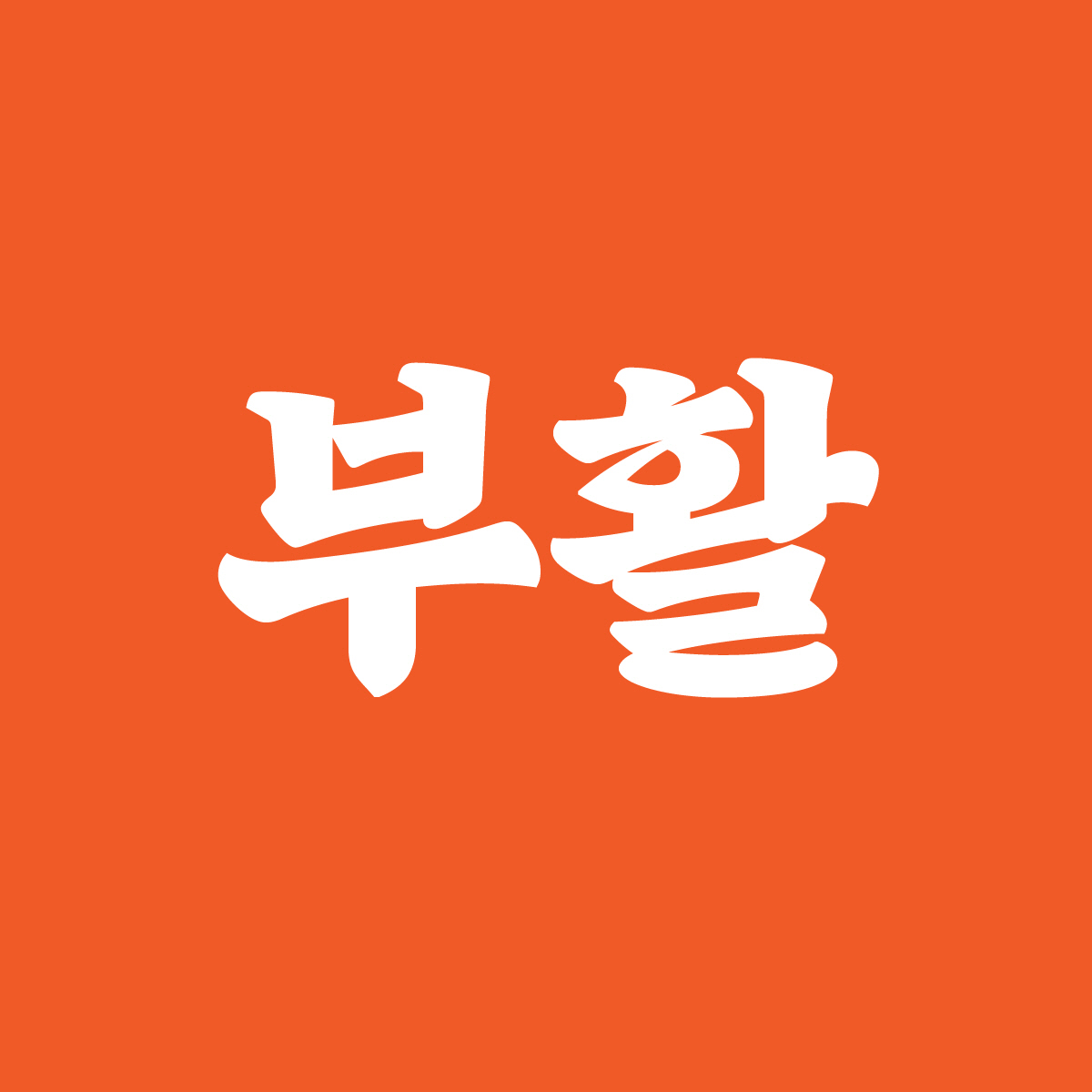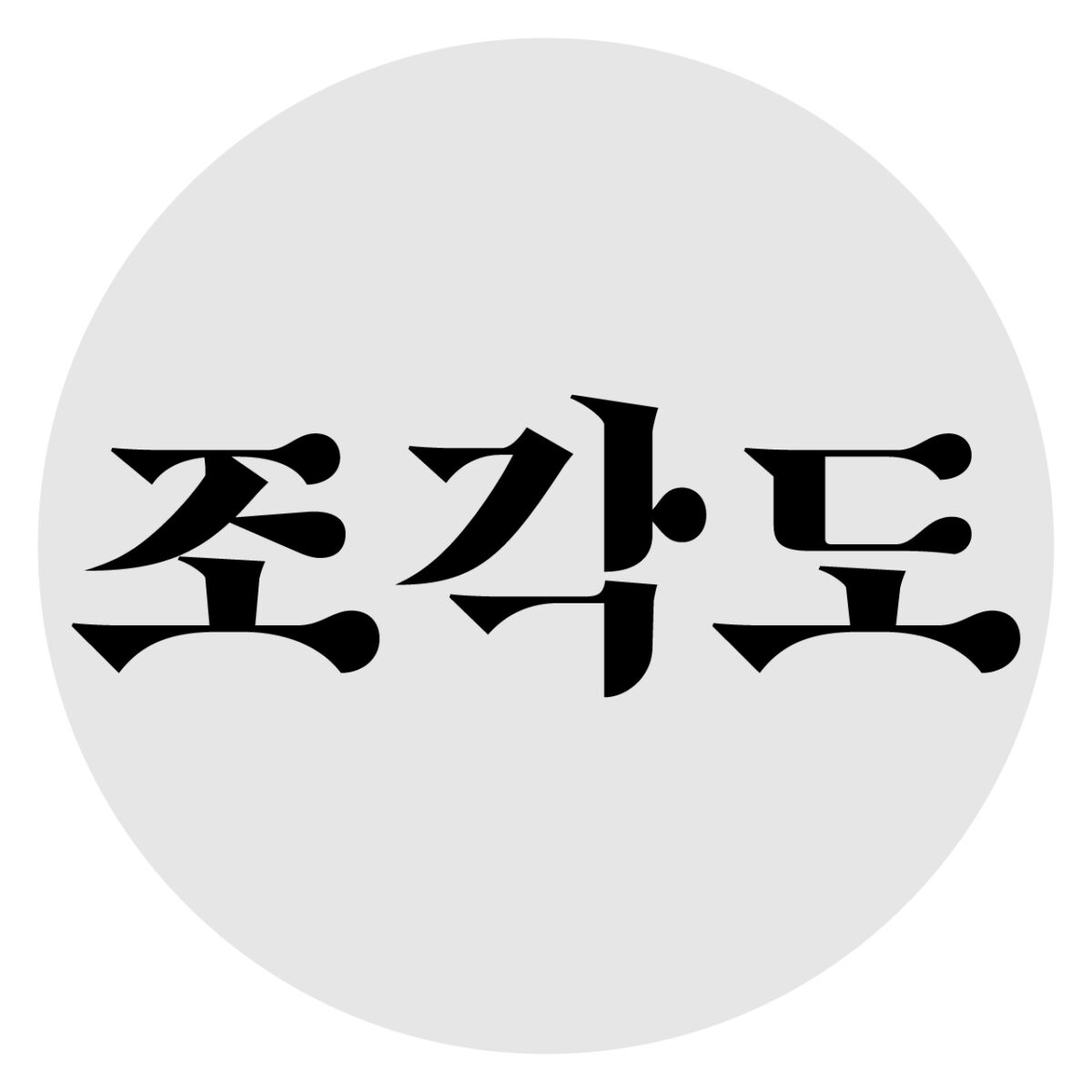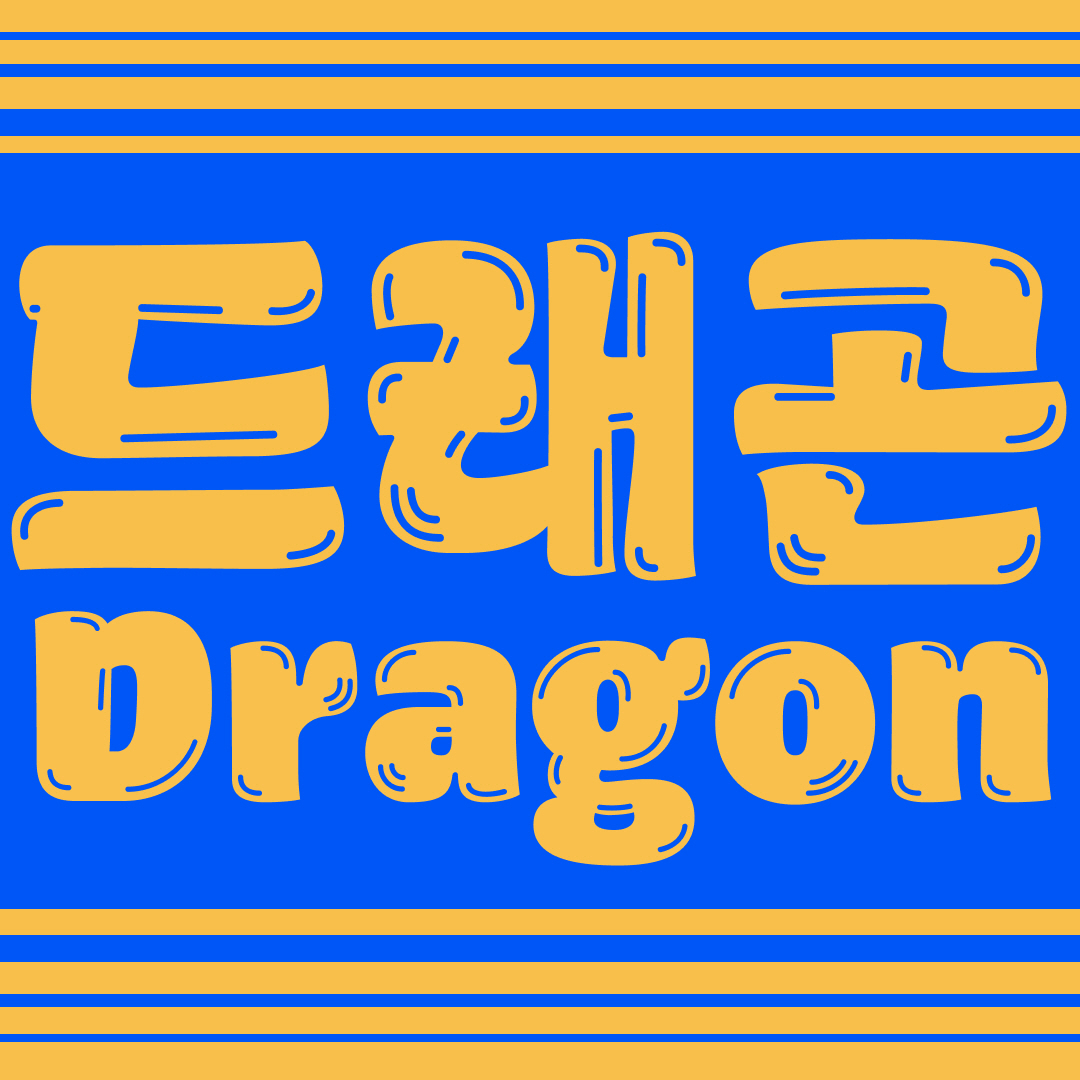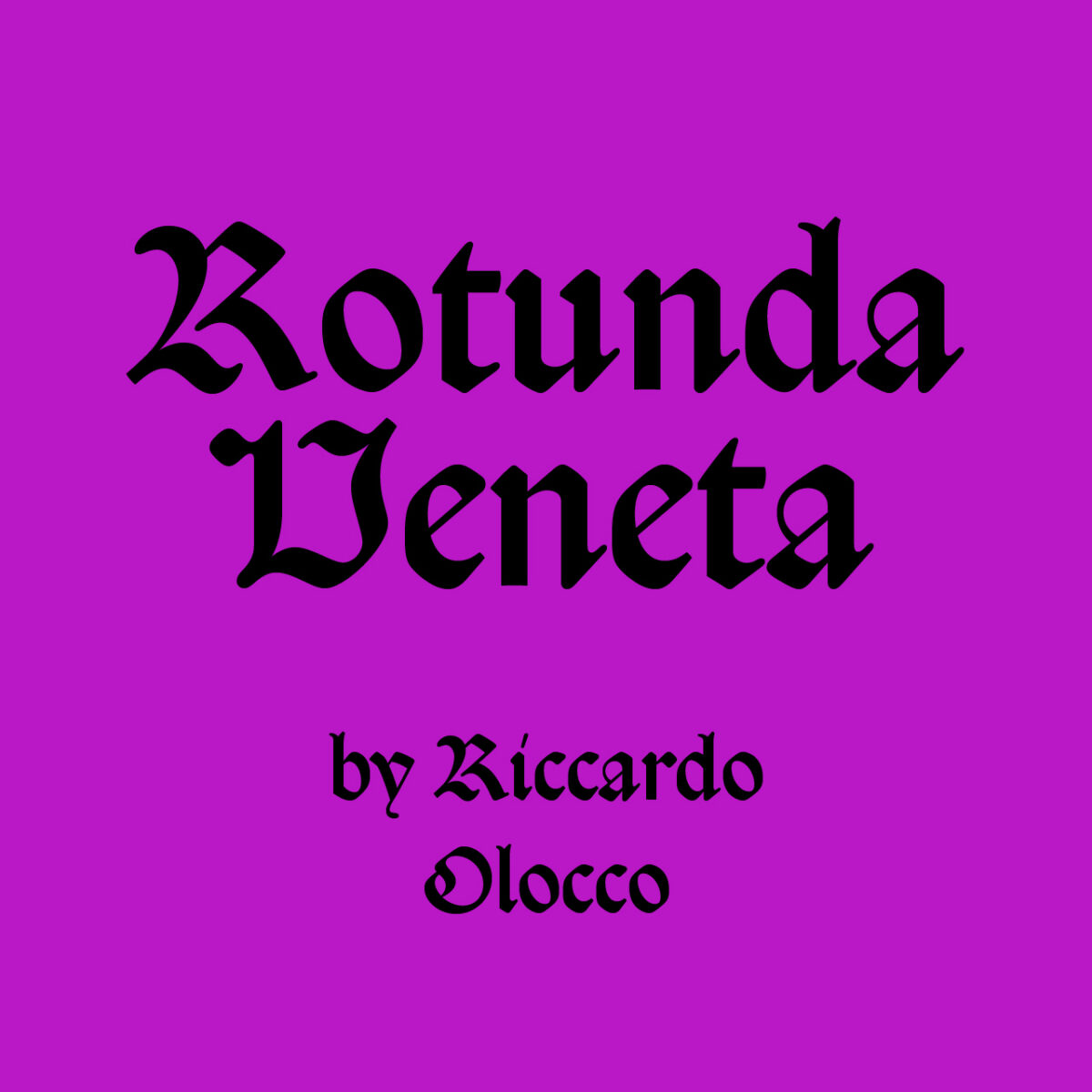
청룡의 해, 용의 기운이 느껴지는 폰트 추천
2024년 1월 산돌구름 추천 폰트 4선
2024년 청룡의 해가 밝았습니다. 청룡의 밝고 활기 넘치는 기운을 전달할 수 있도록 산돌구름이 힘찬 용의 기운을 닮은 폰트 4종을 소개합니다.
1. 티랩 / Tlab부활
「Tlab부활」은 대지 위의 획이 꺾이고, 이동하는 순수한 에너지가 느껴지는 폰트입니다. 우상향하는 기울기가 특징이며, 자소와 자소 간 붓글씨의 흔적이 남아 생동감이 느껴집니다. 오래된 이야기 속에서 부활하는, 장대한 기운이 느껴지는 폰트로 강렬한 텍스트에 사용해보세요!
2. 키그타입 / 조각도
「조각도」는 도검에서 나타나는 강하고 날카로운 인상을 획과 형태의 대비감으로 풀어낸 디스플레이용 폰트입니다. 날카롭고 둥근 부분이 공존하여, 마치 용의 뾰족한 발톱과 곡선의 형태를 연상시키는 것 같아요. 기본적으로 굵은 ExtraBold 웨이트를 지원하며, 도트 스타일로 표현된 3가지 Dot 웨이트까지 제공하여 크게 쓸수록 매력도가 높아지는 폰트입니다. 대형 포스터나 출판물에 조각도를 사용하여, 강한 용의 기운을 느껴보세요.
3. 함민주 / 드래곤
이름부터 용의 콘셉트를 가져온, 발랄하고 명랑한 「드래곤」 입니다. 앞서 본 폰트와 다르게, 둥글고 유기적인 형태로 조금 더 귀여운 인상을 가지고 있어요. 청룡의 해, 따뜻하고 쾌활한 메시지를 전달하고 싶을 때 드래곤을 사용해보세요. 기본 웨이트에 추가로 Highlight 장식까지 제공하니, 어렵게 디자인하지 말고 폰트 하나만으로 명랑한 작업물을 만들어보세요!
4. 캐스트 / Rotunda Veneta
Rotunda Veneta는 르네상스 시기의 고전적인 스타일을 바탕으로 제작된 폰트로, 옛날 이야기 속 상상의 동물인 용의 이미지와 잘 어울리는 폰트입니다. 장식적이고 화려하지만, 정교한 필기체 스타일의 디스플레이 폰트가 필요할 때 Rotunda Veneta를 활용해보세요. 특히 시대적인 배경이 중요한 출판, 인쇄물에 활용하면 그 효과를 200% 높여줄 수 있어요.